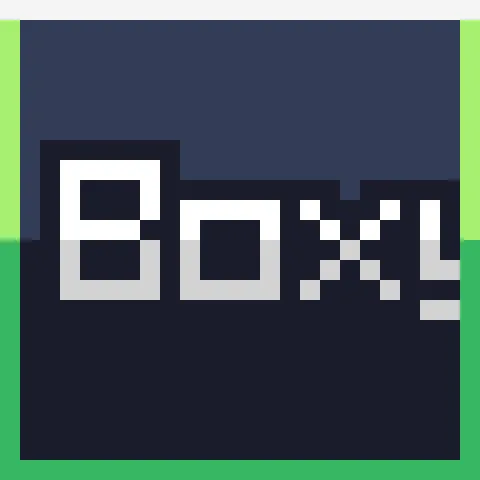
Slyme's Boxy Font
Шрифт с острыми углами и ретро-стилем, похожий на Mojangles, но более чёткий. Простой и совместимый с несколькими версиями Minecraft.
Этот ресурспак представляет собой шрифт с острыми углами, придающий игре ретро-атмосферу. Он заостряет углы на большинстве букв, создавая более резкий и стилизованный вид.